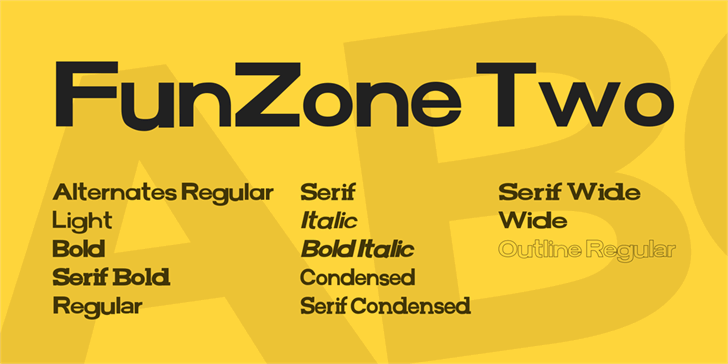
FunZone Two font family
A FunZone Two é uma família de fontes sans-serif criada por Hamilton no ano de 2013 para a plataforma 538Fonts. Inspirada na logo da Teapigs, esta família traz um toque moderno e divertido para qualquer projeto, especialmente aqueles que buscam uma solução versátil sem perder o brilho característico dos logos de marcas. Como uma evolução do FunZone original lançado dois anos antes, FunZone Two oferece mais opções com seu total de 13 fontes distintas e variadas, cada uma capaz de se adequar perfeitamente a diversos estilos de design. Seja para criar um site profissional ou uma identidade visual única, a FunZone Two é uma escolha inteligente que certamente irá tornar seu trabalho mais atraente e moderno.